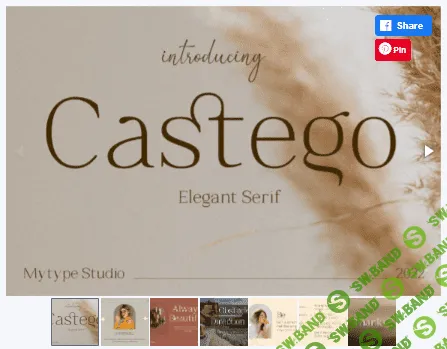
Название: Castego Font (2022)
[creativefabrica] Castego Font (2022)
Castego — это современный шрифт с засечками, который воплощает элегантность и шарм в каждом символе. Он идеально подходит для роскошных логотипов, брендинга, стильного редакционного дизайна, женских журналов, косметических брендов, рекламных дизайнов, индустрии моды и многого другого.